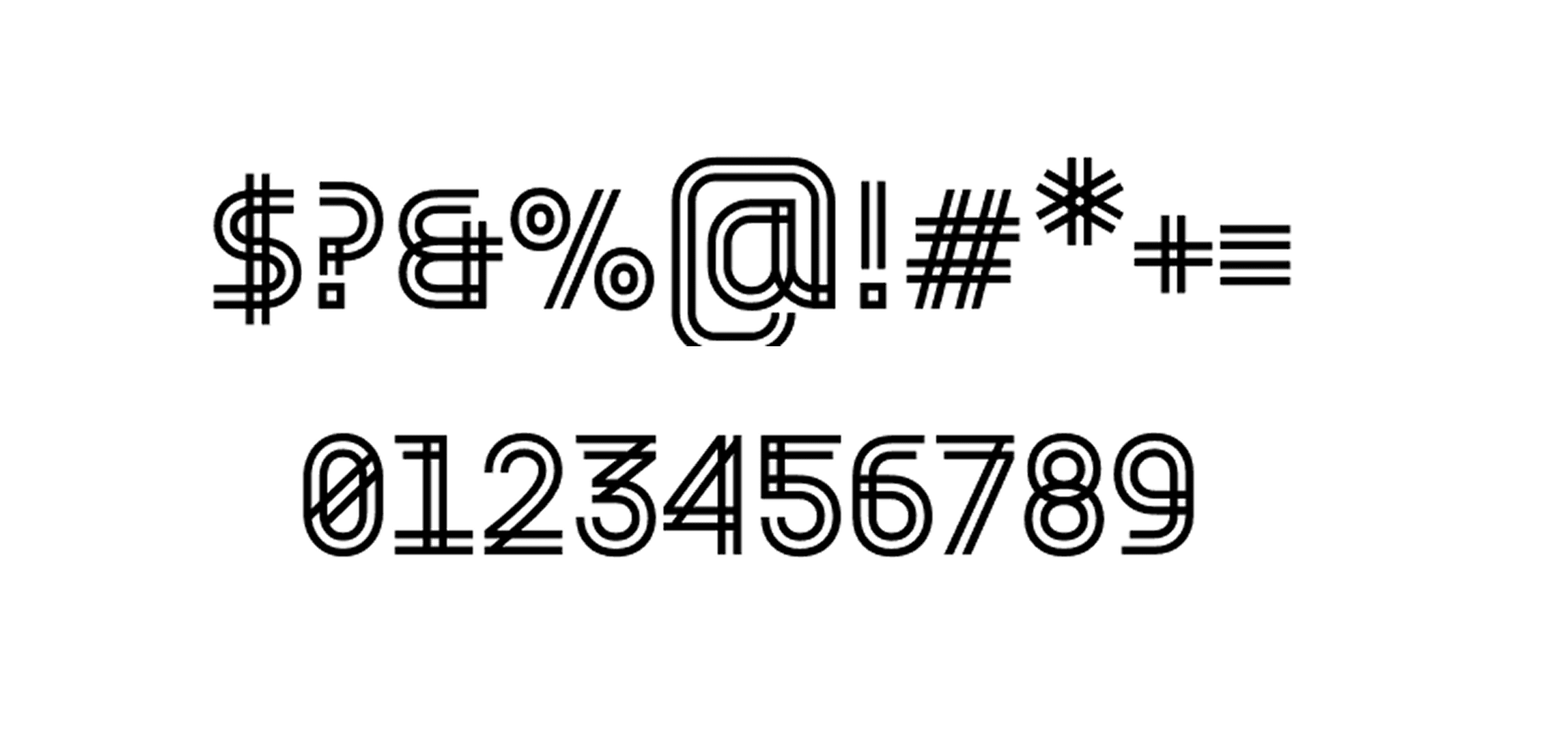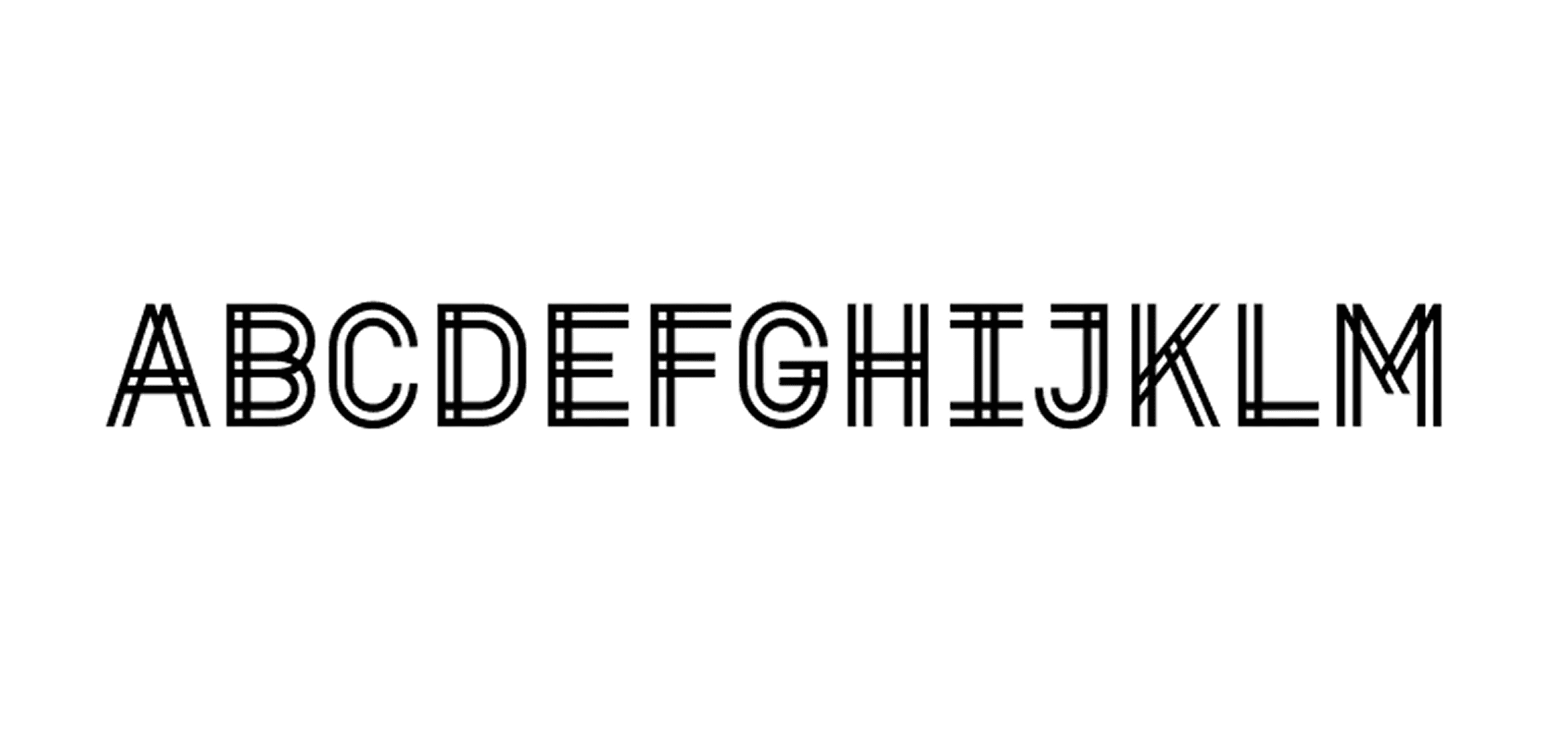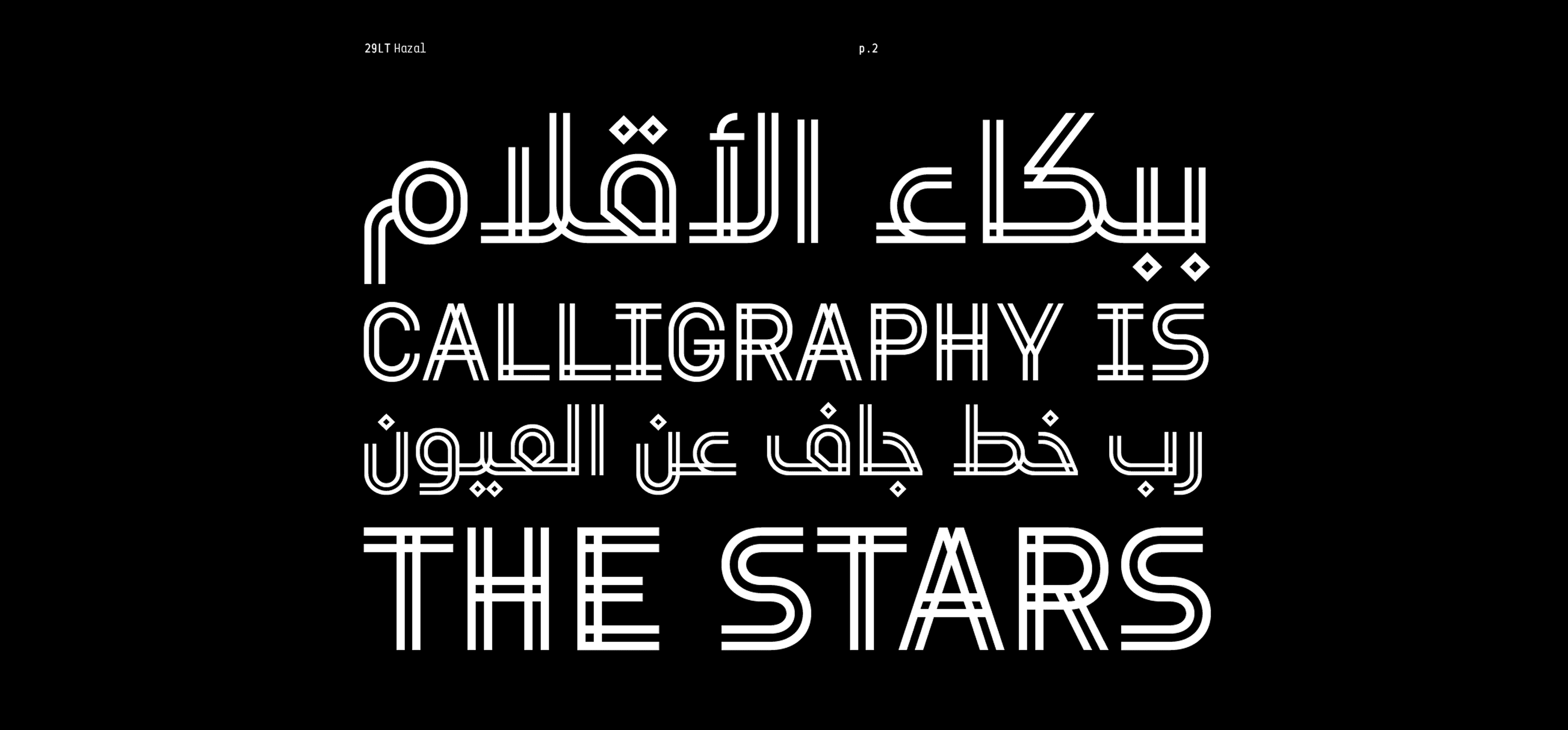
هزال هو خط هندسي تم تصميمه بخطّين متوازيين، يجمع بين الأحرف اللاتينية الكبيرة (All-Caps) والخط العربي الهندسي. يظهر التأثير المتبادل بين اللغتين بوضوح في التصميم. يعكس هذا الخط روح المرح والحيوية، ويعد خيارًا مثاليًا لإضفاء طاقة مرئية على أي تصميم.